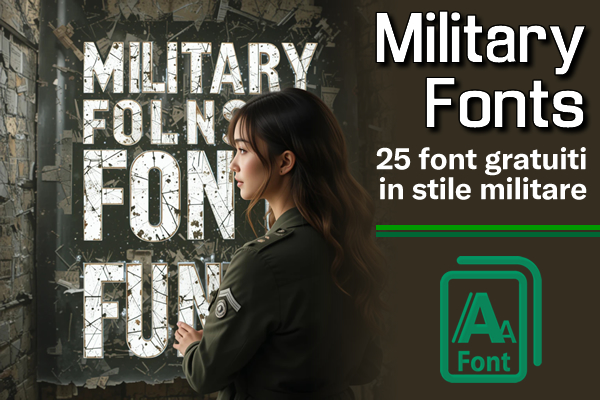
Quando si tratta di progettare grafica che trasmette forza, disciplina e autorità , i caratteri militari si distinguono come un'ottima scelta. Questi font sono ampiamente utilizzati in branding, poster, videogiochi e media relativi alle forze armate, offrendo un'estetica dominante che attira istantaneamente l'attenzione.
I font militari sono caratteri tipografici ispirati alle lettere stencil che si vedono su veicoli militari, uniformi ed equipaggiamenti. Spesso presentano lettere in grassetto e a blocchi con spigoli vivi o disegni a stencil ritagliati, che riflettono utilità e durata. Questo stile evoca un senso di ordine, rendendoli perfetti per progetti che devono comunicare forza e affidabilità .
Military Fonts : 25 font gratuiti in stile militare